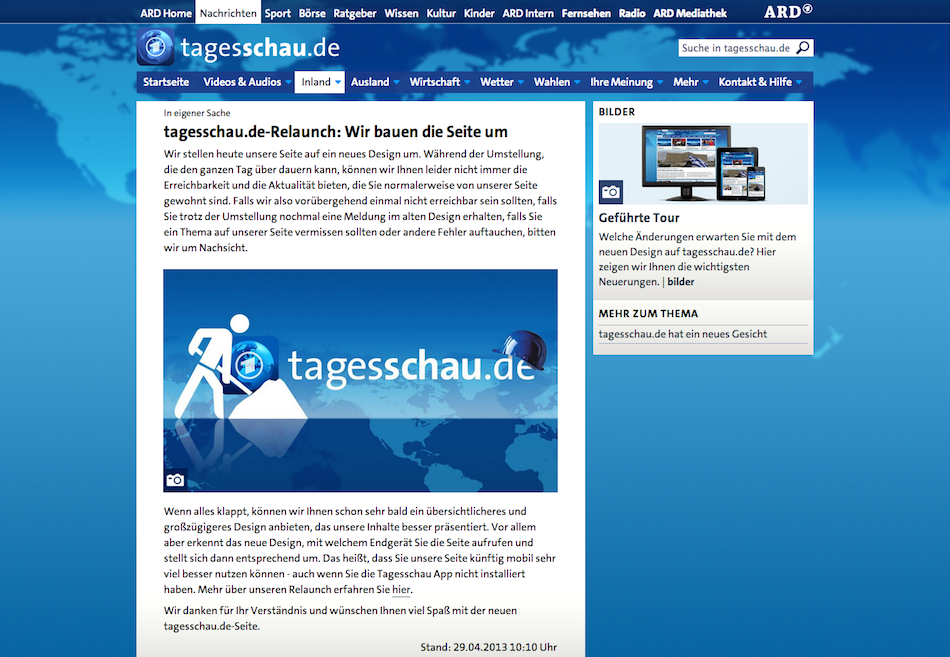
Neue Tagesschauseite
Heute ging die Tagesschau mit einem neuen Design online …
Was sagt ihr dazu? Ich finde es im Headerbereich etwas eng. Die obere Leiste durch dunklere Farbe und eine Haarline abzugrenzen gefällt mir aber es hätte insgesamt doch mehr Luft haben können oder?
Aufgeräumt sieht es aus, kein überflüssiger Schnickschnack da, das ist positiv anzumerken. Die Haarlinie oben wirkt durch ihre geringe Stärke allerdings fast wie ein Fehler auf mich, da könnte es gerne etwas luftiger zugehen. Der Textsatz wirkt auf den ersten Blick etwas plump, aber das kann täuschen. Ich muss die Seite bei Gelegenheit mal genauer unter die Lupe nehmen.  :-)
Mach das mal bin gespannt auf dein Urteil — und das der anderen natürlich …
Was mir gerade noch aufgefallen ist, ist dass die obere Menüzeile, die ja sowas wie eine Sparte wählbar macht etwas dezenter hinterlegt sein könnte, weil sie ja kein Hauptmenü ist. Vielleicht könnte man die Haarline an der Stelle des ausgewählten Punktes einfach dicker machen …
je nach Browsergröße … verschiedene Darstellungen
Das nennt sich responsive web design und sorgt dafür, dass eine Website auch bei verschiedensten Fenstergrößen noch optimal funktioniert. Für eine so wichtige Medien-Website eigentlich ein Muss. Bravo! :biglove: :biglove:
Und bei der Beurteilung beachten, dass hier quasi 8 farblich und grafisch durchaus unterschiedlich anmutende Markenauftritte unter einer gemeinsamen Dachmarke vereint sind. Ich finde das Ergebnis sehr, sehr ansprechend.
Kritteleien der Art "man hätte dieses Element auch 1px breiter" oder "jenen Farbton auch eine Spur gesättigter verwenden können" ohne Argument, warum die getroffene Wahl nicht gut war ... nun, die fallen bei mir dann eher unter Meinung denn unter Kritik. A bisserl kleinkariert.
btw: die Haarlinie unter der Topnavi funktioniert in meinen Augen auf 6 der 8 Unterseiten bestens. Das sind genau die 6 Seiten, die ob ihrer farblichen Gestaltung die Haarlinie benötigen, um die Topnavi sicher vom Rest zu trennen.   Steff
klar ist das meine Meinung, ich bespreche aber sowas hier weniger, um die Macher der Seite zu kritisieren sonder vielmehr um was zu lernen und zu sehen, ob mein kritisches Auge mit „hier zu wenig Luft“ auch „Recht“ hat – Stichwort: aus den Fehlern anderer Lernen ;-)
Kritteleien der Art "man hätte dieses Element auch 1px breiter" oder "jenen Farbton auch eine Spur gesättigter verwenden können" ohne Argument, warum die getroffene Wahl nicht gut war ... nun, die fallen bei mir dann eher unter Meinung denn unter Kritik. A bisserl kleinkariert. (Steff11)
Für den Fall, dass Du mich ansprichst: Ich habe einen Grund genannt: Auf mich wirkt die zarte Haarlinie fast wie ein Fehler, »Blitzer« würde man im Printbereich dazu sagen. Und das war durchaus sachlich gemeint.
Natürlich kann man auch an einem solch großen, inhaltlich hochkomplexen Webauftritt eine Meinung zu Details äußern. Mir scheinen solche gestalterischen Feinheiten aber in diesem Fall wirklich nachrangig gegenüber der Beurteilung, wie stimmig das Gesamtkonzept ist, wie sicher und schnell man seine Zielinhalte findet, und vor allem heute, in Zeiten einer immer unübersichtlicher werdenden Zahl von Endgeräteformaten: wie gut funktioniert die Seite auf unterschiedlichsten Displays. Das schwebte mir im Kopf bei der harten Wahl "kleinkariert". Wenn ich von der Seite was lernen wollte, dann erstmal stundenlang an der Navigationsstruktur, zuallerletzt an solchen Details.
Nochmal zur Linie: mir scheinen 1px-Linien eine der allerselbstverständlichsten Mittel im Webdesign zu sein, um die Abgrenzung unterschiedlich genutzter Bereiche dezent aber erkennbar zu halten, bisweilen auch wie hier, um die Abgrenzung ähnlich-farblicher Bereiche fein zu verstärken. Zumeist aber doch als dunklere Linie vor hellerem Hintergrund. Hier nun trifft der ungewöhnlichere Fall vielleicht auf eine deformation-professionnelle von Printgestaltern, die feine helle Konturen auf dunklem Hintergrund möglicherweise (ich mutmaße, da nicht vom Fach) eher meiden, weils schwer zu drucken ist und das umgekehrt dann halt vorwiegend als Blitzer des versehentlich unbedruckten weißen Papiers kennen.
Ich hab die Linie grad fix mal testweise im Photoshop auf 2px weiß gesetzt. Wär mir persönlich schon zu dominant.
lg, Steff
nochwas: durchaus erstaunt bin ich, wie sauber die TheSans in allen möglichen Zoomstufen am Bildschirm funktioniert.
Ich bin eher enttäuscht. Die Monitorversion (nur diese hab ich mir angeschaut) ist ein Sammelsurium einzelner Designs und es fehlt die Klammer außenrum, die klarmacht, dass das alles innerhalb der ARD stattfindet. Das Menü am oberen Rand kann das allein nicht leisten.
Die Auto-Schrift ist viel zu groß. Damit geht viel Inhalt auf dem Bildschirm verloren, der eigentlich hätte dargestellt werden können. Eine Anpassung der Schriftgröße fehlt leider völlig – die Umschaltung Auto, XS … XL bringt mich auf dem Monitor auch nicht weiter, weil sich dann eben auch die Darstellungsbreite verringert.
tagesschau.de ist von allen die unübersichtlichste – genau das Gegenteil dessen, was eine Nachrichtenseite leisten muss. Der blaue Menübalken geht dank mangelnder Abgrenzung im Hintergund unter, die unmotiviert im Hintergrund platzierte Weltkarte bringt nur Unruhe. "Kontrast" und "Augenführung" sind Fremdworte. Das Logo auch noch auf die Weltkarte zu stellen ist schon jenseits von grenzwertig. Dabei hab ich noch halbwegs gute Augen – ich wäre auf einen Feldtest mit der Hauptnutzergruppe gespannt gewesen, aber nun ist’s ja schon ausgerollt.